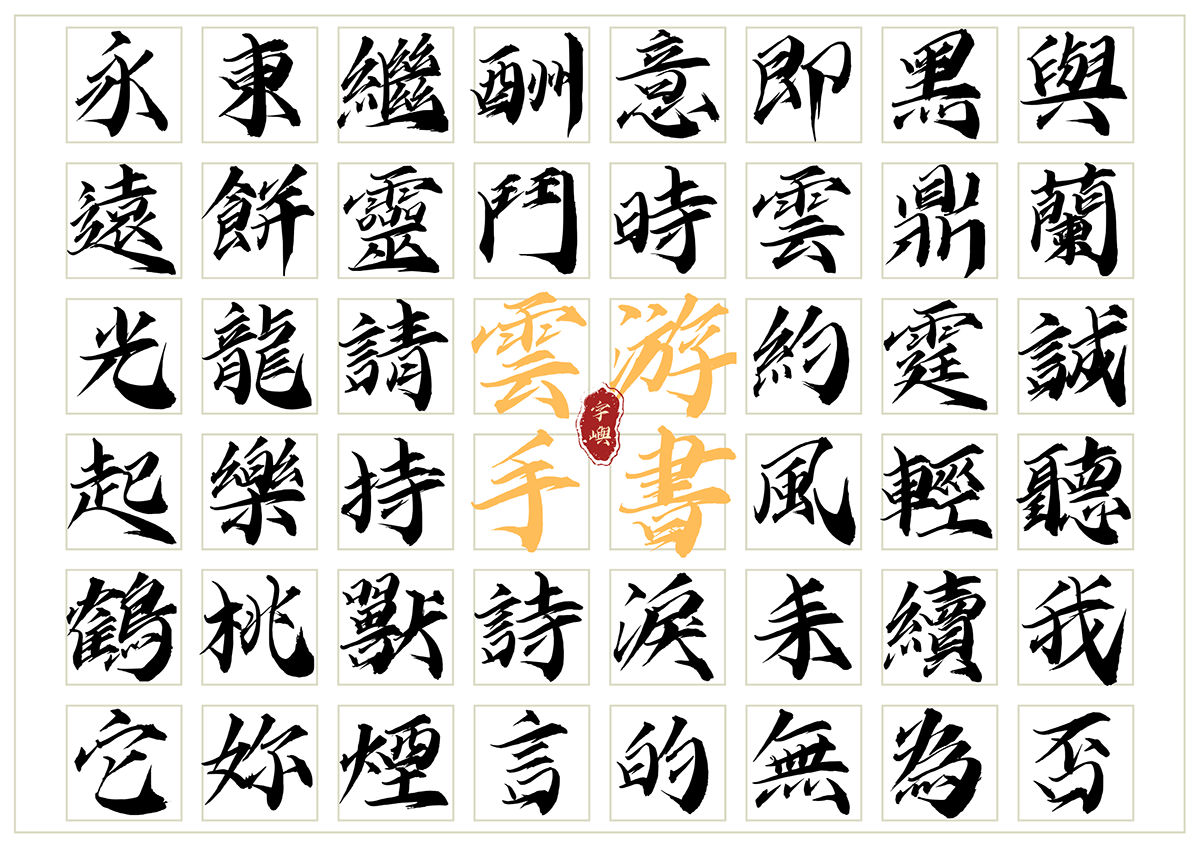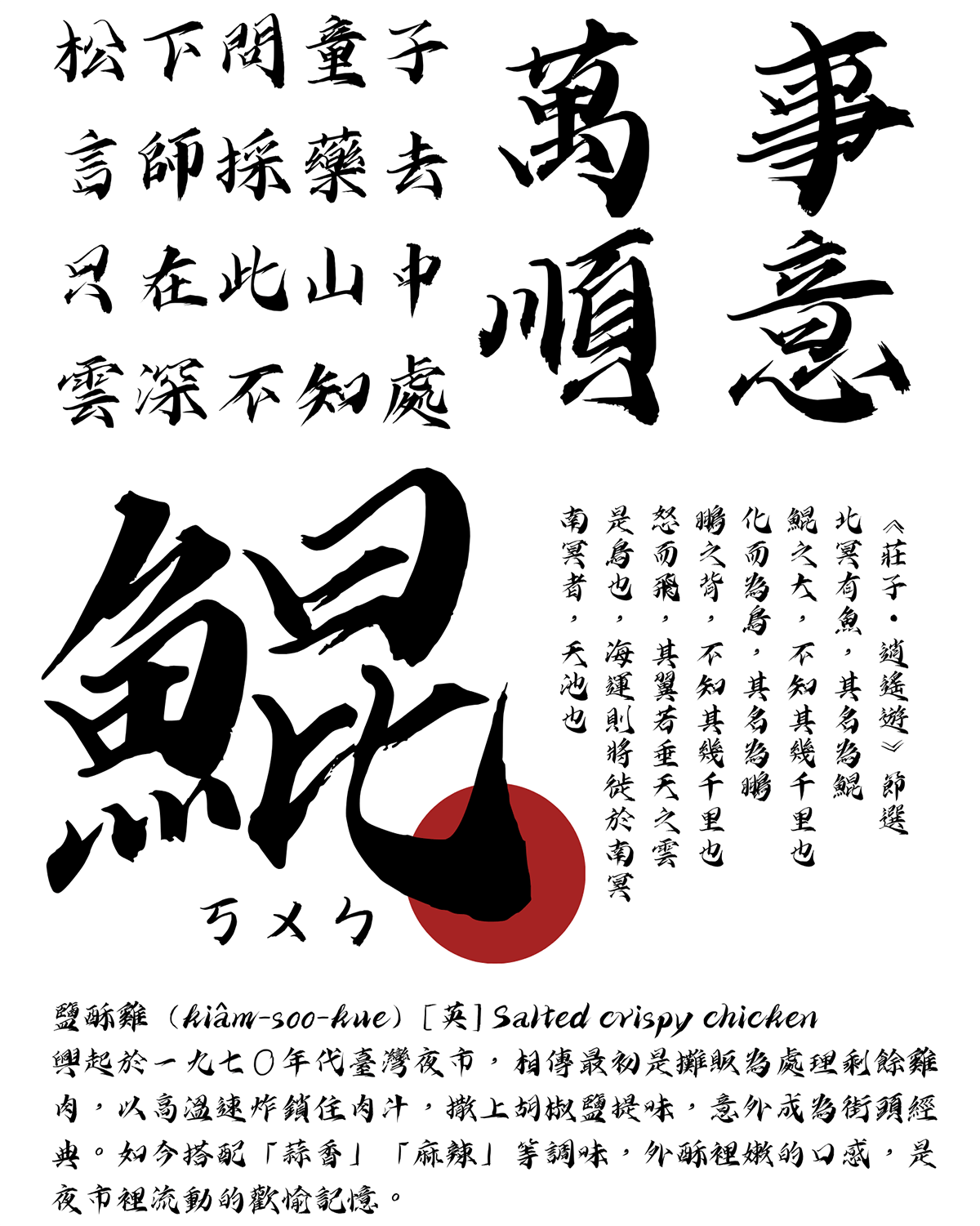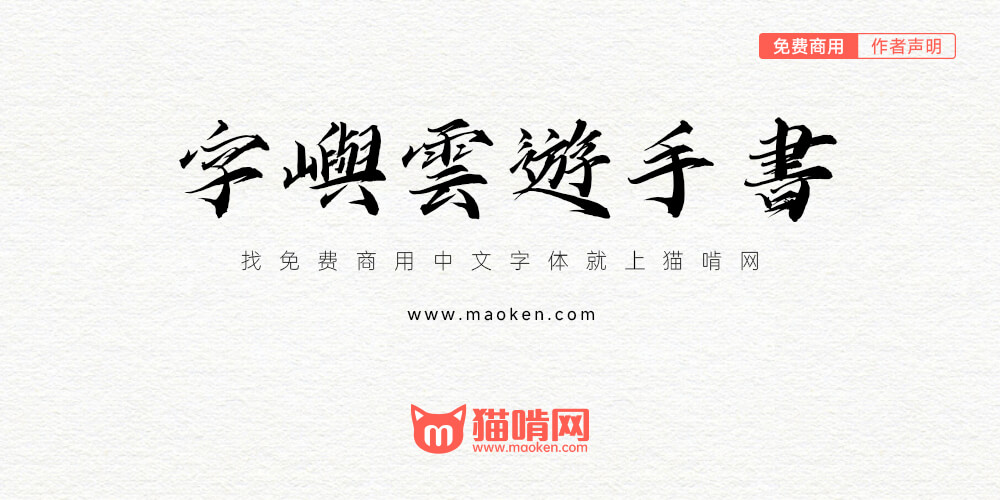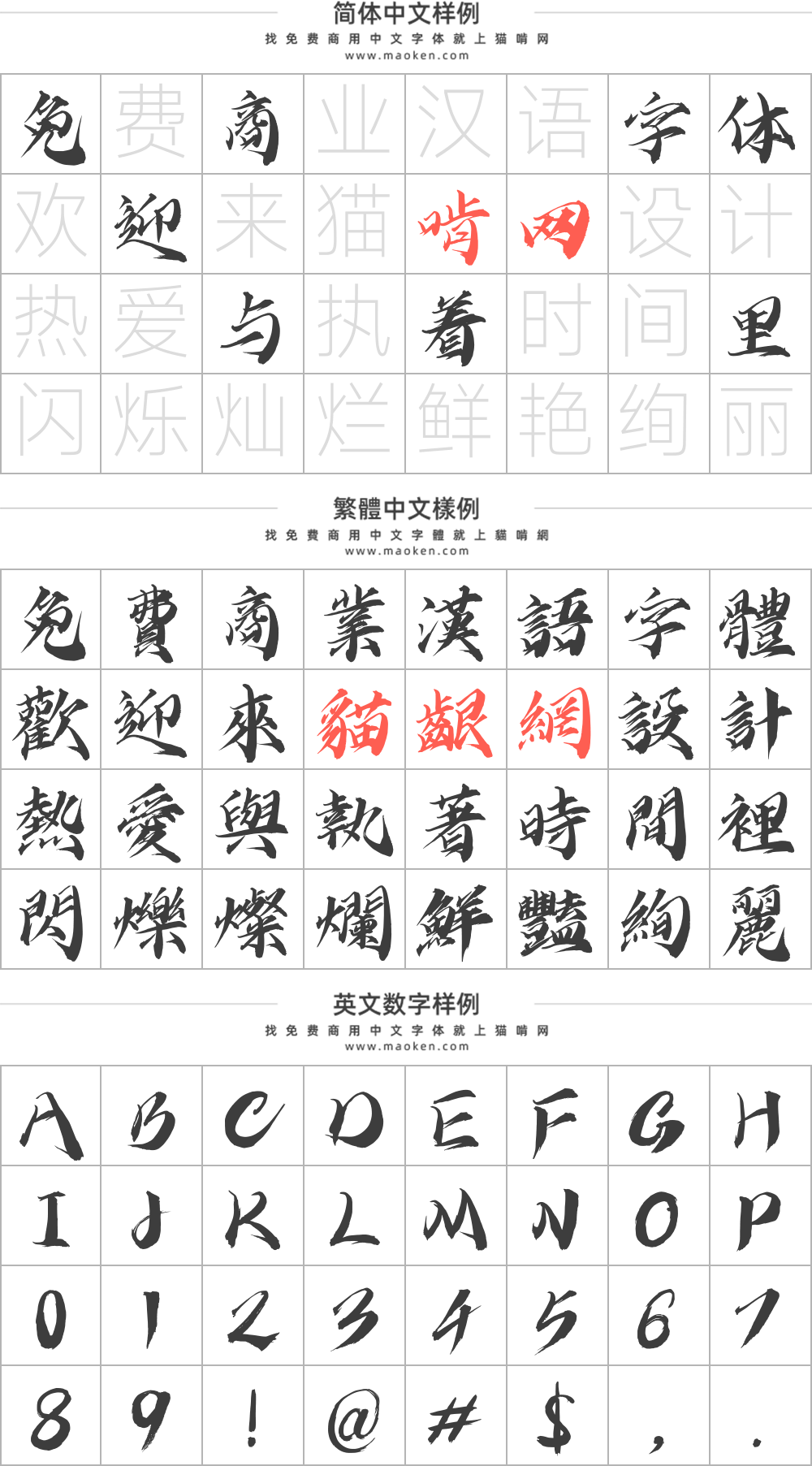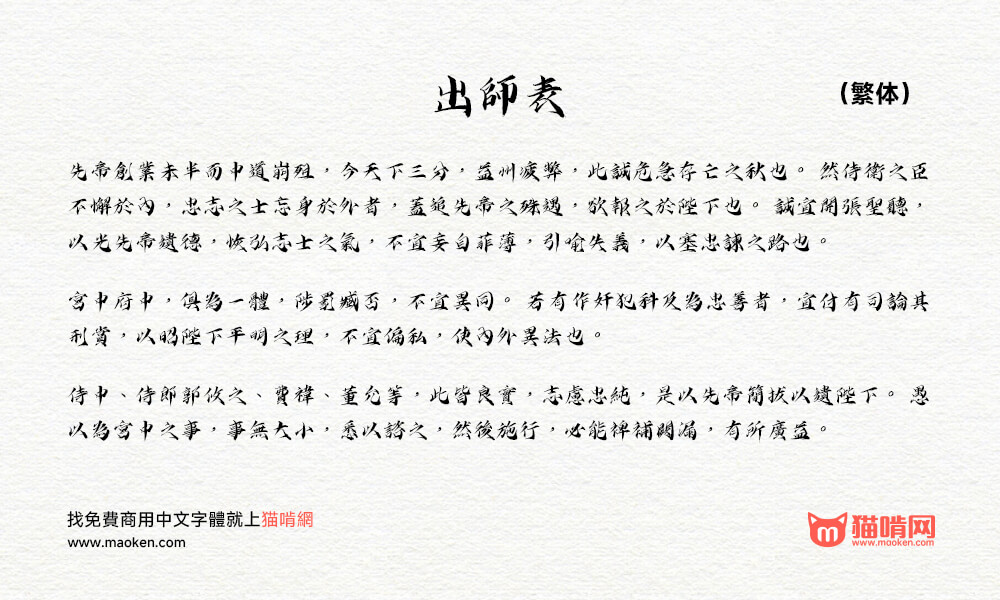
字屿云游手书:字屿第一款免费可商用字型
字体作者:字屿 (中国台湾) 字体字重:1个
字嶼雲遊手書」整体字势开合揖让得宜,腾挪转折间,不致过于纤秀婉约,婉转中犹见铿锵力道,锋芒尽显。透过局部形变与笔势外拓,叠加出整体气势,兼顾阴柔与阳刚、含蓄与强劲之美。露锋用笔贯穿字体始终,结体紧致,大量曲线更强化字势动感与字形张力,恰似流云萦绕剑锋,飘逸中蕴藏锐劲。
以台语常用标准汉字为标准,参考jf7000字集,包括注音符号、欧文字符、阿拉伯数字和标点符号,总字符约7640字以上。
我们希望这款字有无限的可能性:
• 国潮文创:手帐封面题字、刺绣吊饰文字
• 茶饮与伴手礼:珍珠奶茶杯身题字、凤梨酥礼盒侧边文案
• 出版领域:乡土神话故事集、山林散文选的封面与章节标题
• 影视动画:仙侠剧开场片名、庙宇场景牌匾题字
• 户外广告:古迹园区导览牌、文创商圈灯箱
• 传统服饰:庙会常见的服饰刺绣文字、改良旗袍腰带印字
• 文博展览:特展海报、老街文物说明卡
• 品牌识别:中药行招牌、台式茶馆
• 工艺饰品:陶瓷茶具底款、珊瑚吊坠刻字
这江湖体可真江湖
这是iSlide云犹体的繁体版
• 简体就是‘iSlide云犹体’,猫啃就有收录
• 2个名字差的有点大啊。。。而且感觉繁体估计修过比简体好看点。
• 繁体字本身好书写,简体字不好写,所以看起来繁体字比简体好看。